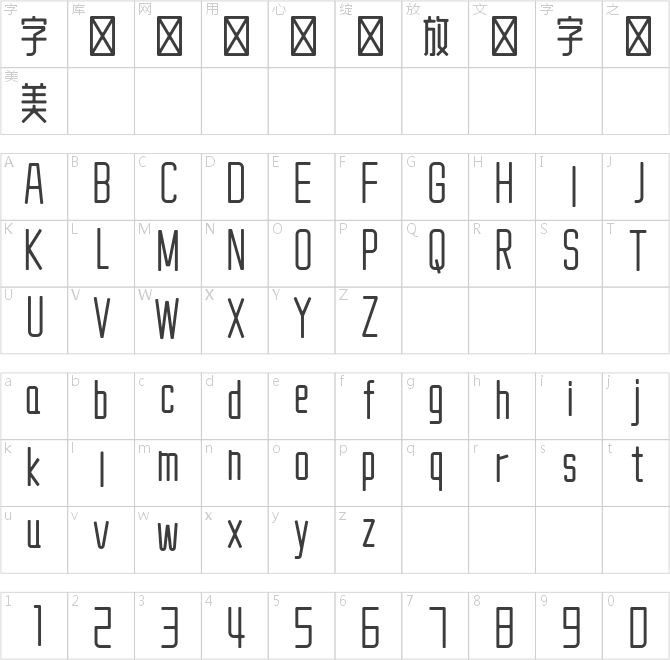
圓體
「 途牛類圓體 」是途牛UED設(shè)計(jì)團(tuán)隊(duì)設(shè)計(jì)的一款字體, 提供1000個(gè)常用字限時(shí)免費(fèi)下載! 這款字體 簡約、輕松、活潑、流暢 ,設(shè)計(jì)感非常強(qiáng),也十分百搭,可惜的是支持的字?jǐn)?shù)太少,缺字太多。別外這款字體雖然是可以免費(fèi)商用的,但是前提是要先關(guān)注他們的公眾號獲得授權(quán)才可以使用哦。微信公眾號請?jiān)谖⑿派纤阉鳌巴九S脩趔w驗(yàn)中心”。本文尾部有公眾的二維碼。